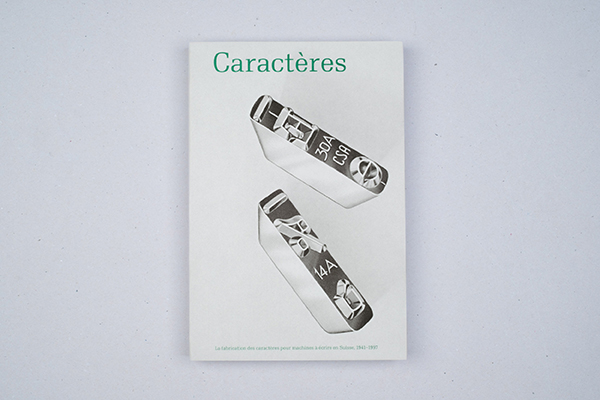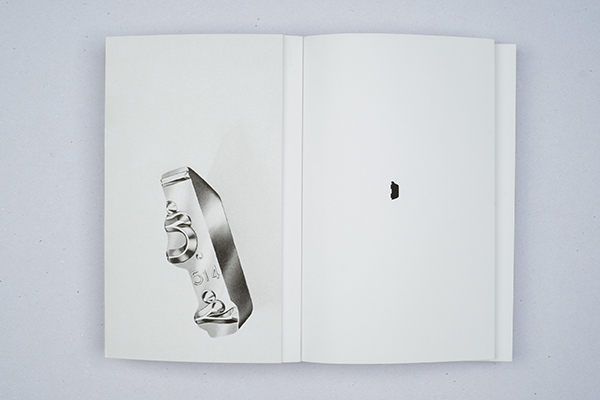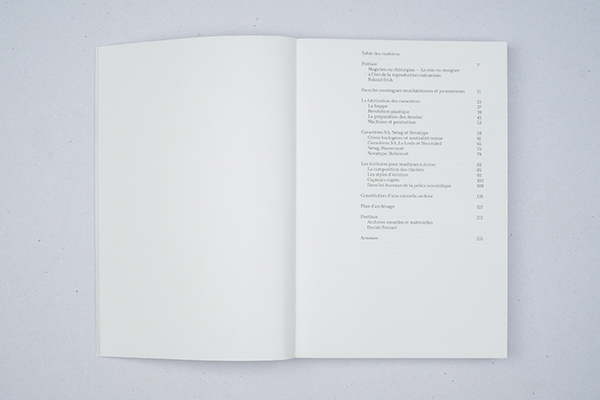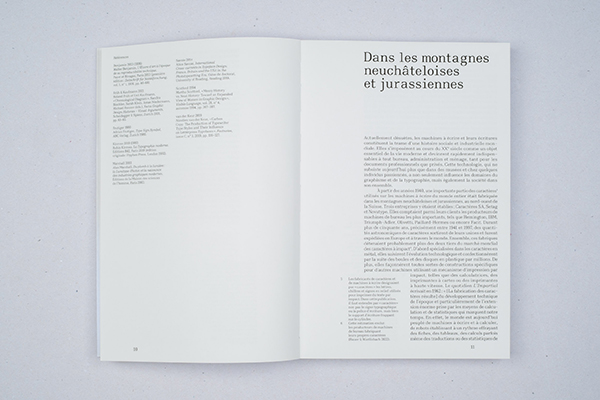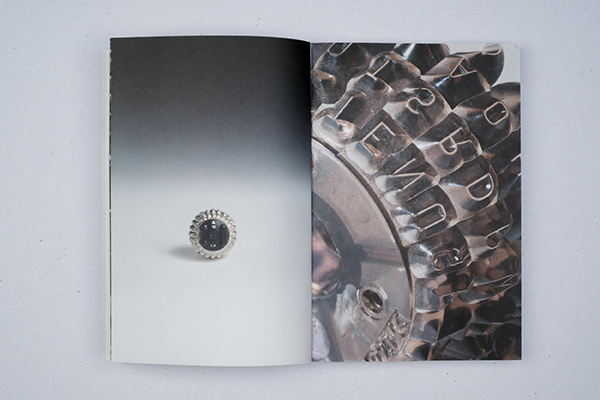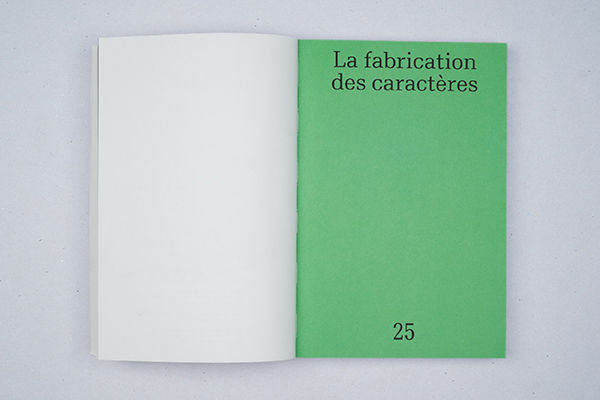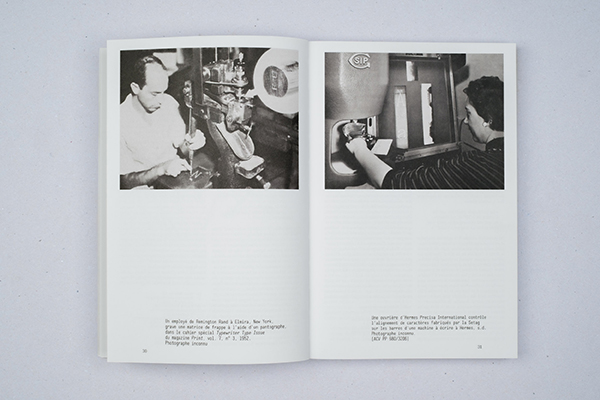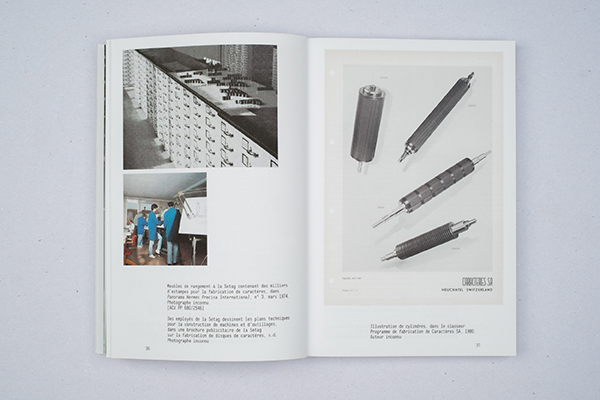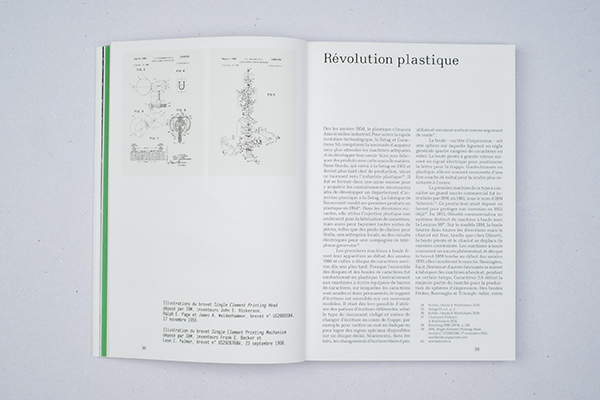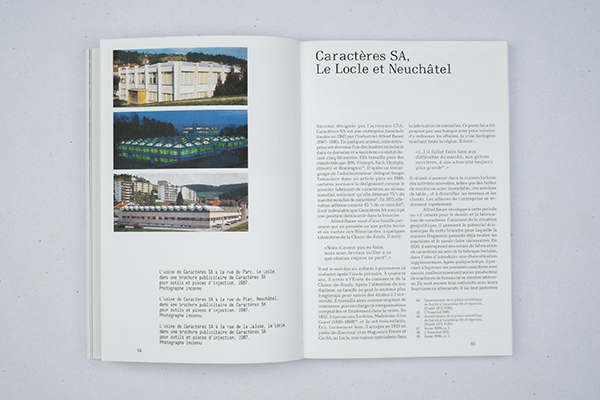
Sophie Wietlisbach (Hrsg.)
Caractères
La fabrication des caractères pour machines à écrire en Suisse, 1941–1997
Französische Ausgabe
Buchgestaltung: Sophie Wietlisbach
• Geschichte und Rolle der Schweizer Schreibmaschinenschriftenhersteller Caractères SA, Setag und Novatype
• Eine Schweizer Industrie- und Typografiegeschichte – reich bebildert mit zahlreichen bisher unveröffentlichten Dokumenten
• #5 der Reihe Visuelle Archive, in Kooperation mit ECAL
Die
drei Unternehmen, die eine führende Position auf dem Weltmarkt
innehatten, waren massgeblich an der Gestaltung, Entwicklung und
Herstellung von Schriftkomponenten und Schriftbildern für
Schreibmaschinen sowie alle Arten von Anschlagdruckern beteiligt. Diese
optisch unverwechselbaren Schriftennehmen in der heutigen typografischen
Szene eine bedeutende Rolle ein.
Die reich
bebilderte Publikation mit den detaillierten Porträts von Caractères SA,
Setag und Novatype erforscht die Geschichte hinter den Schriften und
den historischen Kontext, in dem sie hergestellt wurden. Als die drei
Schweizer Unternehmen in den 1990er-Jahren geschlossen wurden, sind die
meisten ihrer Archive vernichtet worden. Dieses Buch, das die in
jahrelanger Recherche an zahlreichen Orten gesammelten Dokumente und
Informationen zusammenführt, enthält unveröffentlichtes Bildmaterial
und beleuchtet einen wenig bekannten Teil der industriellen und
typografischen Geschichte auf lokaler und internationaler Ebene.
Mit Texten von Sophie Wietlisbach, einem Vorwort von Roland Früh und einem Nachwort von Davide Fornari.